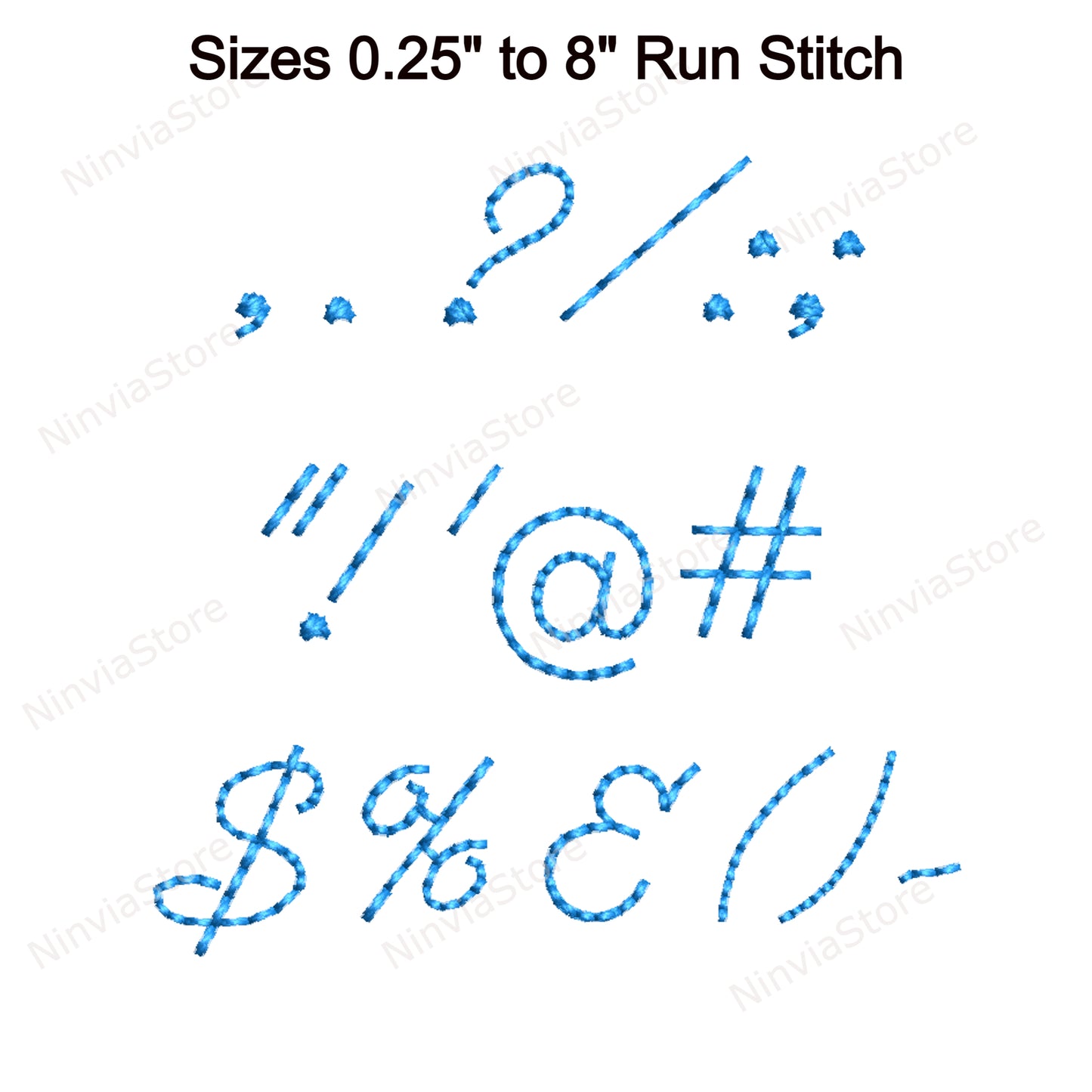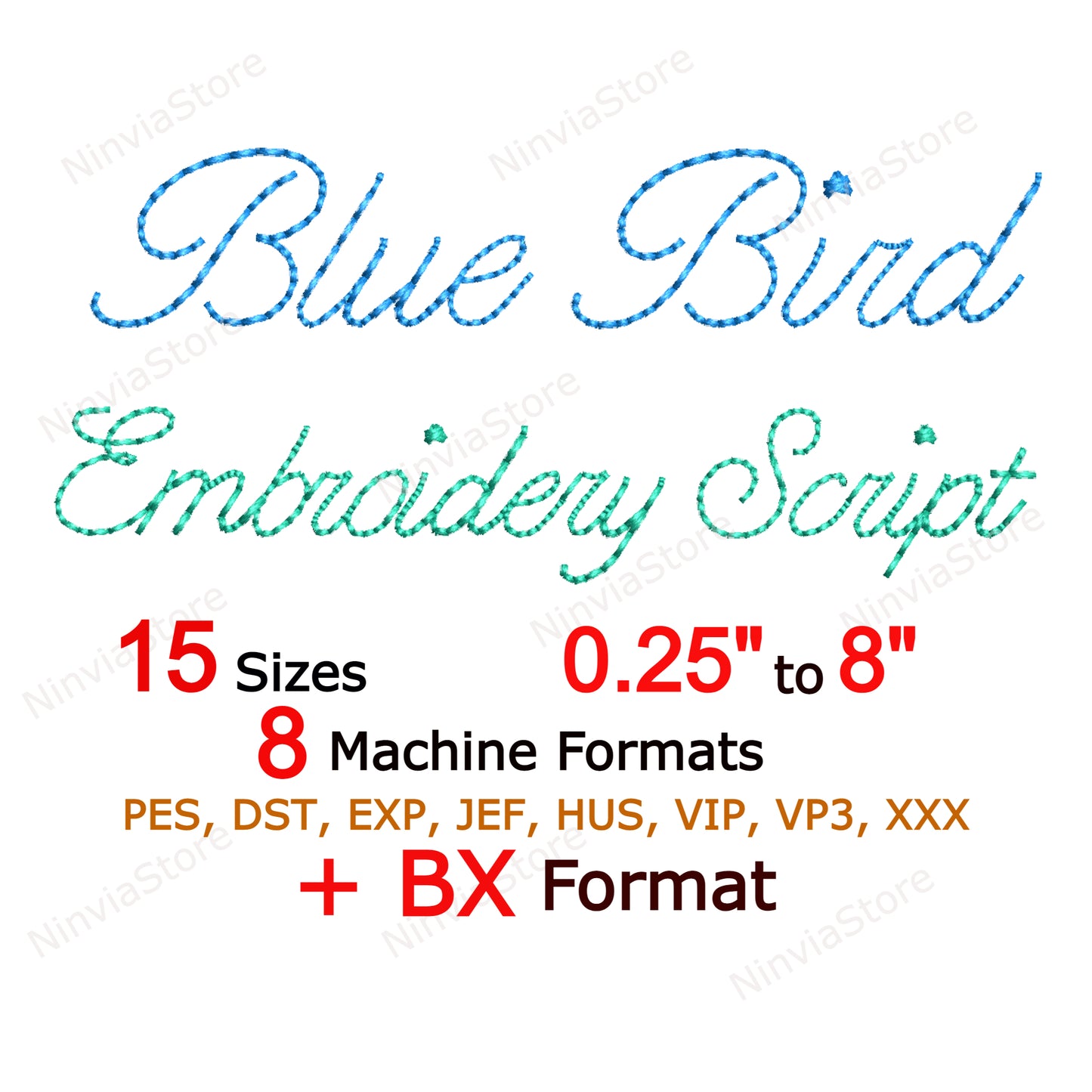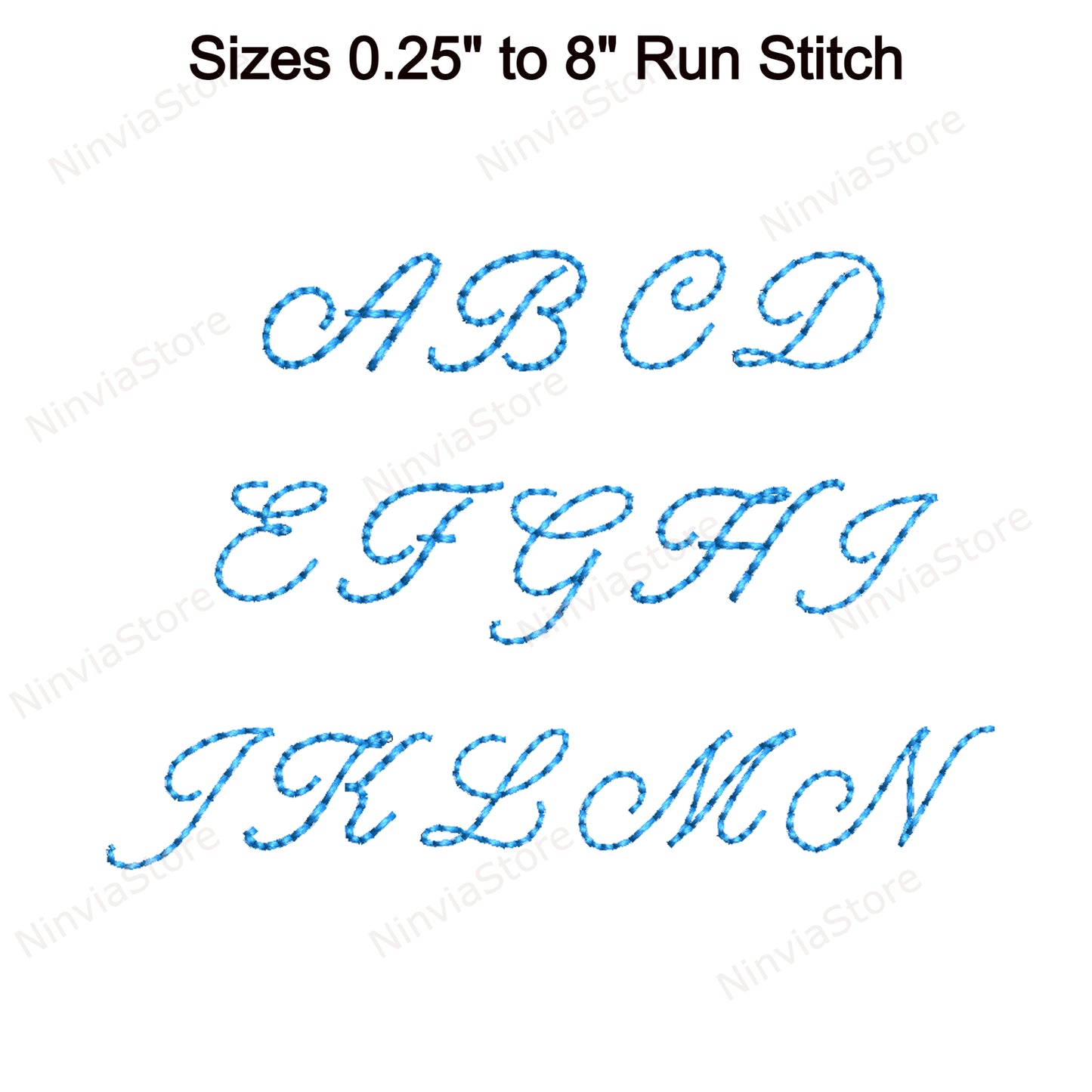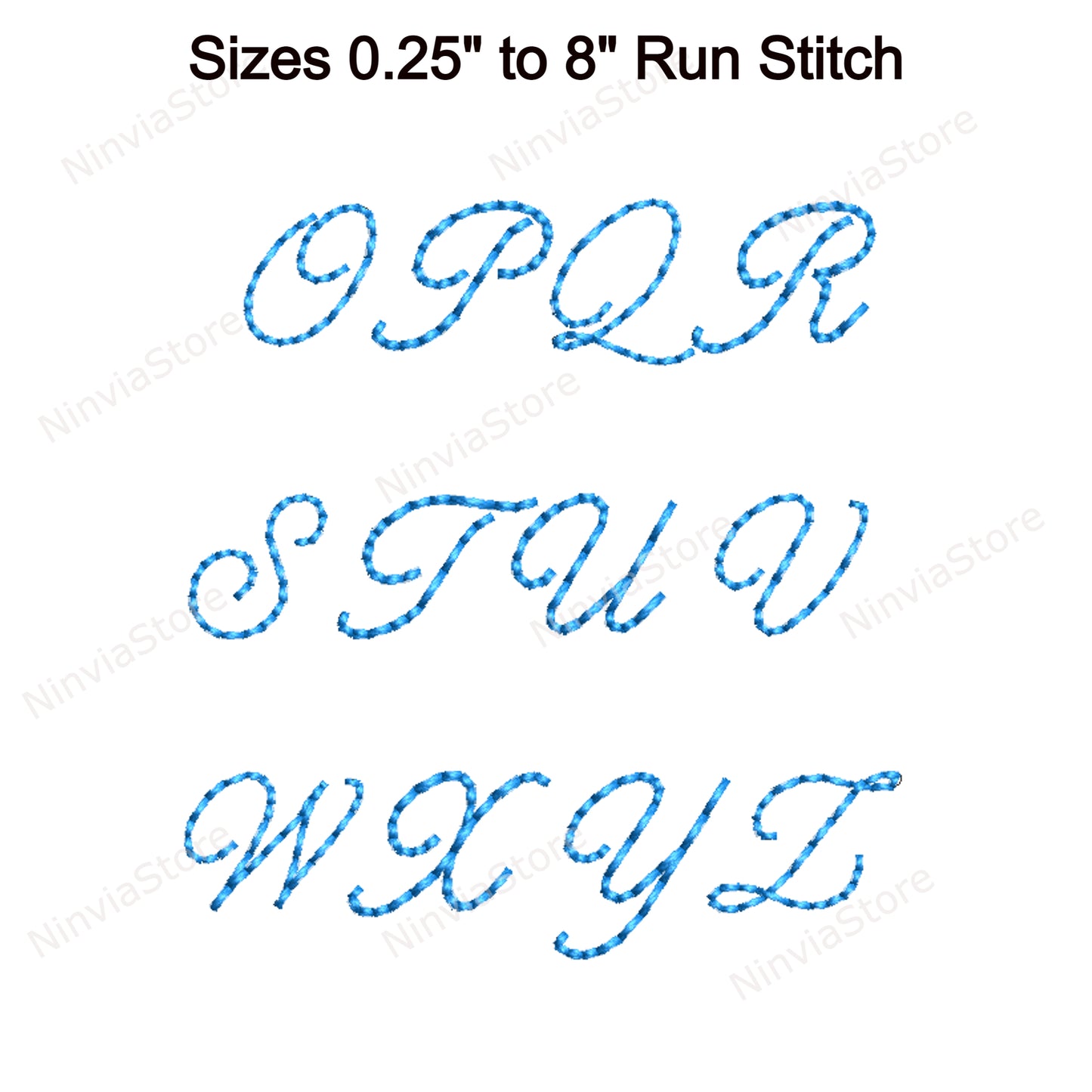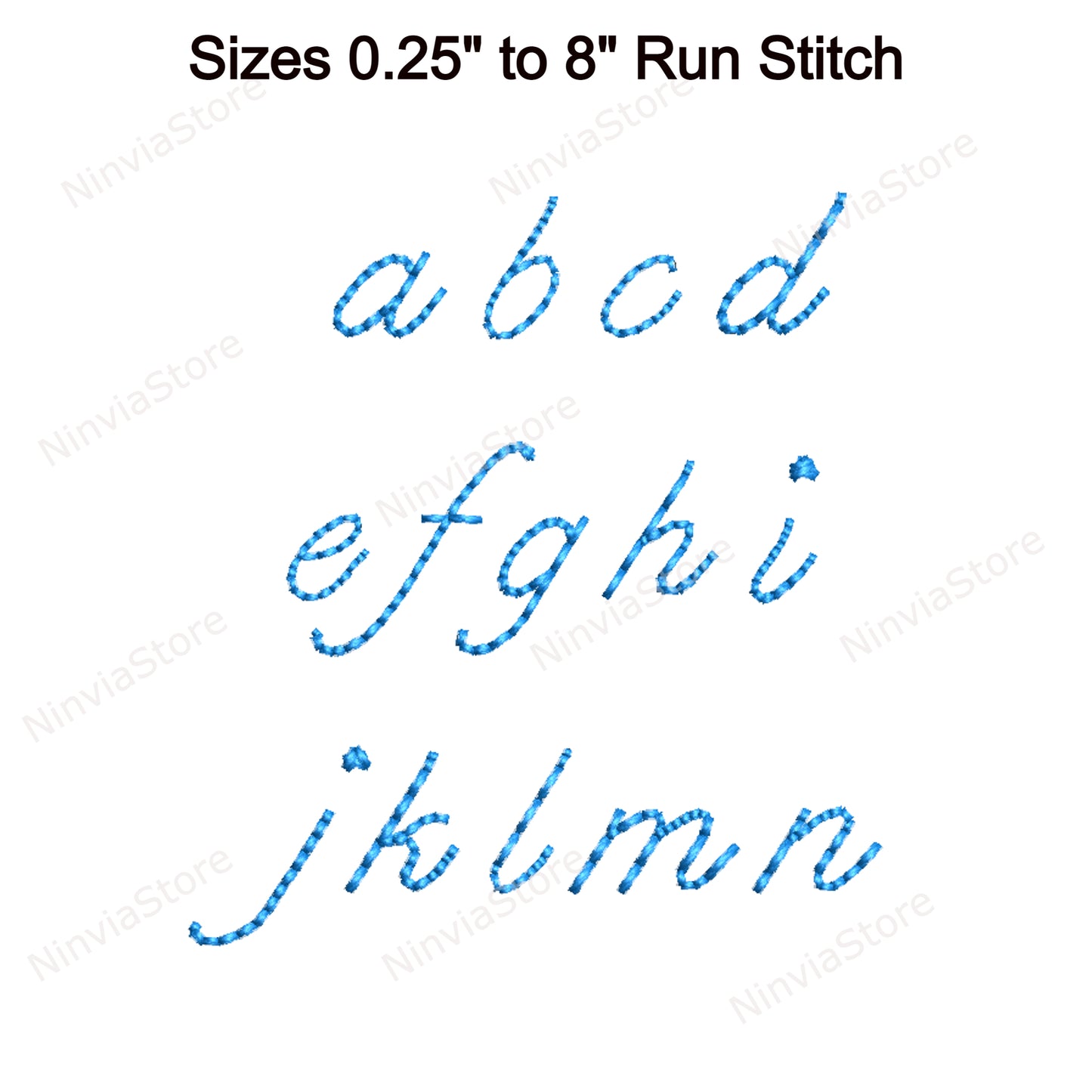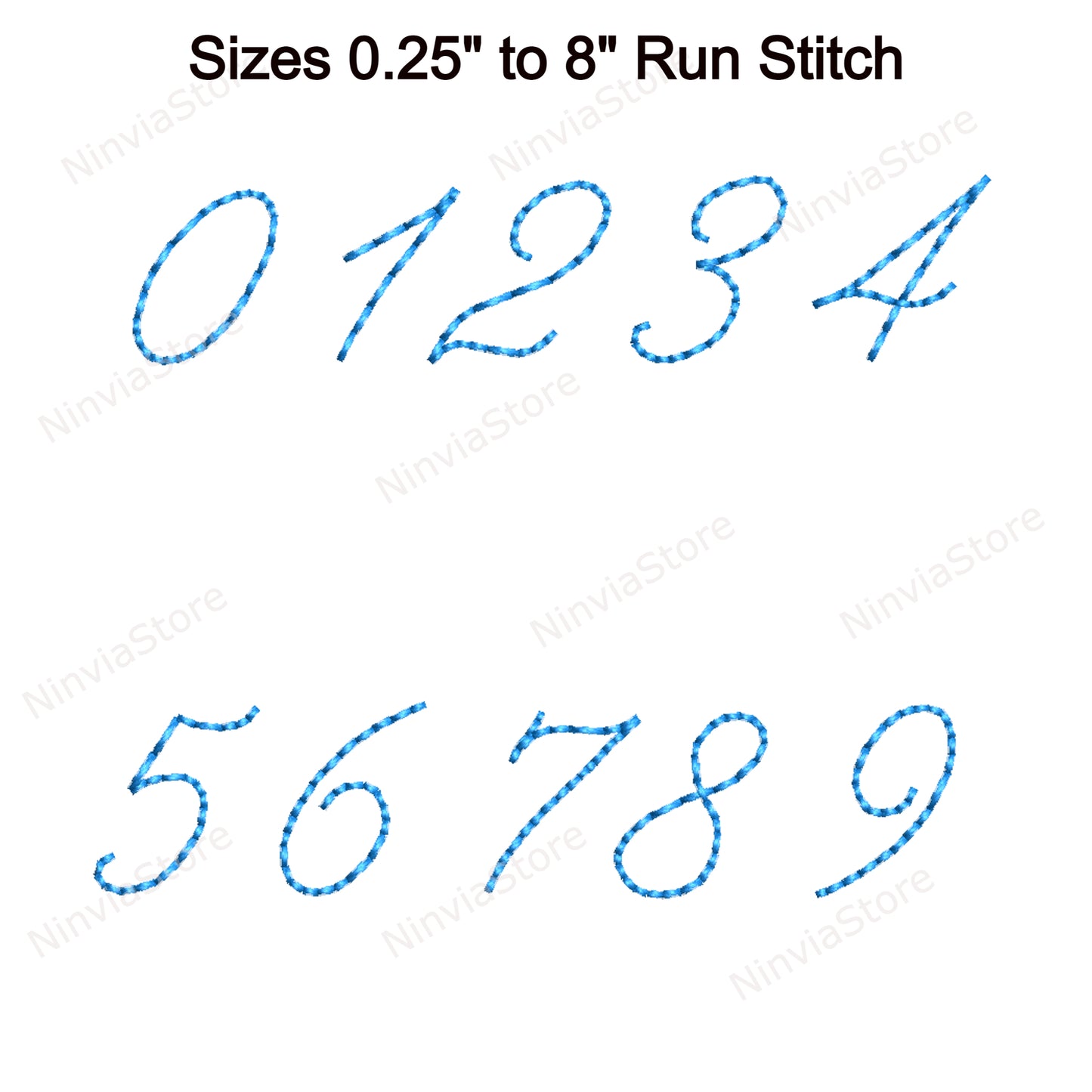
Bean Stitch Script Machine Embroidery Font, 15 tailles, 8 formats, Ballantines BX Font, Run Stitch PE police, Monogram Alphabet Broderie Designs
UN POINT TRIPLE PASSAGE